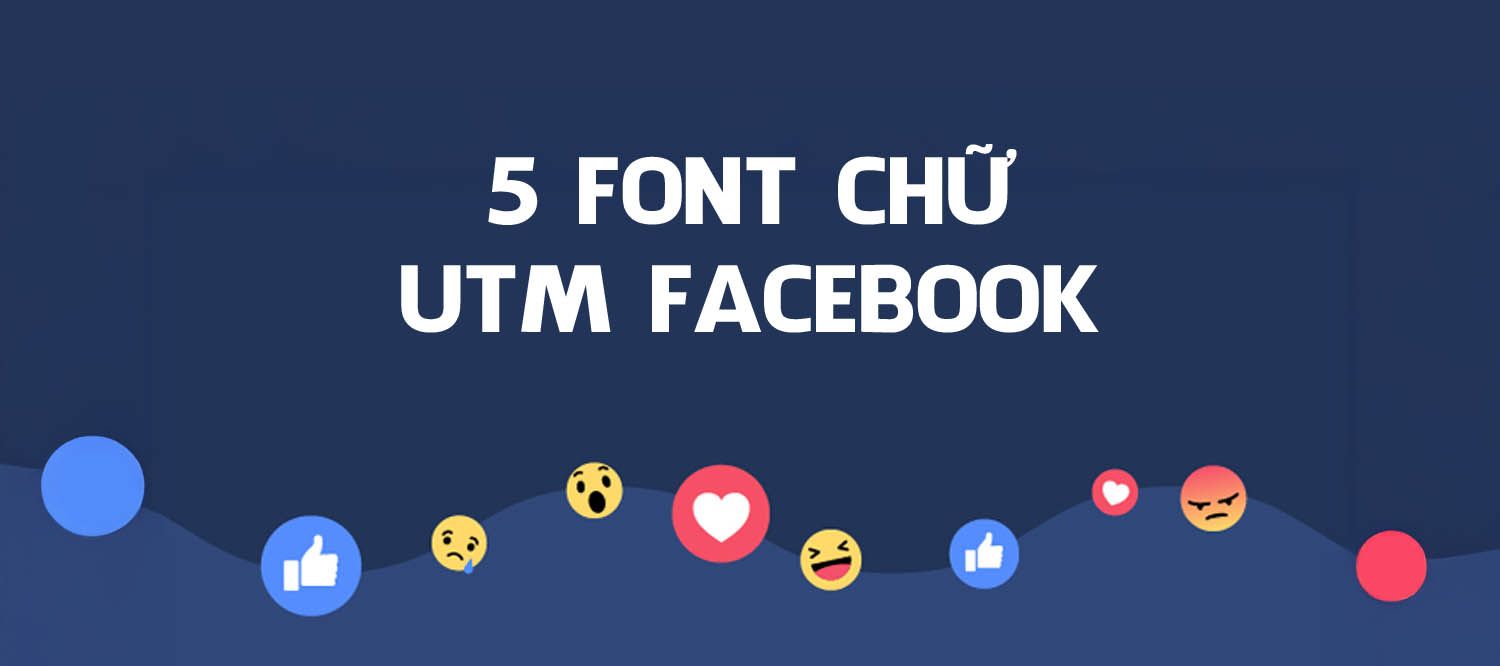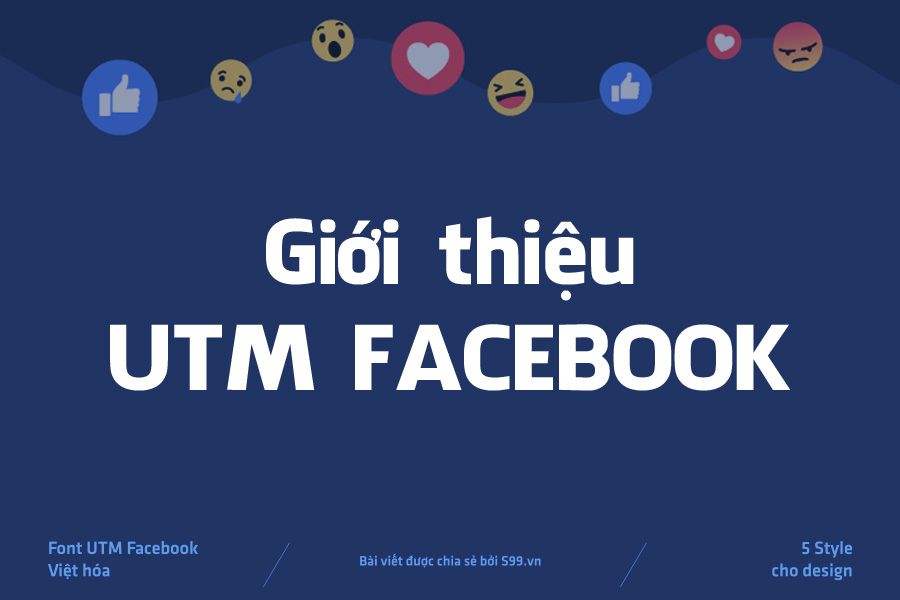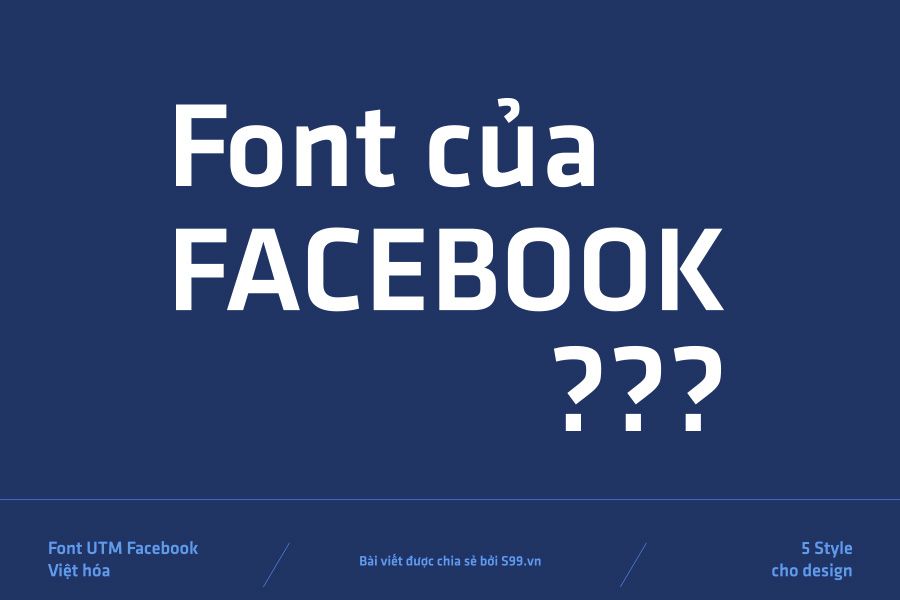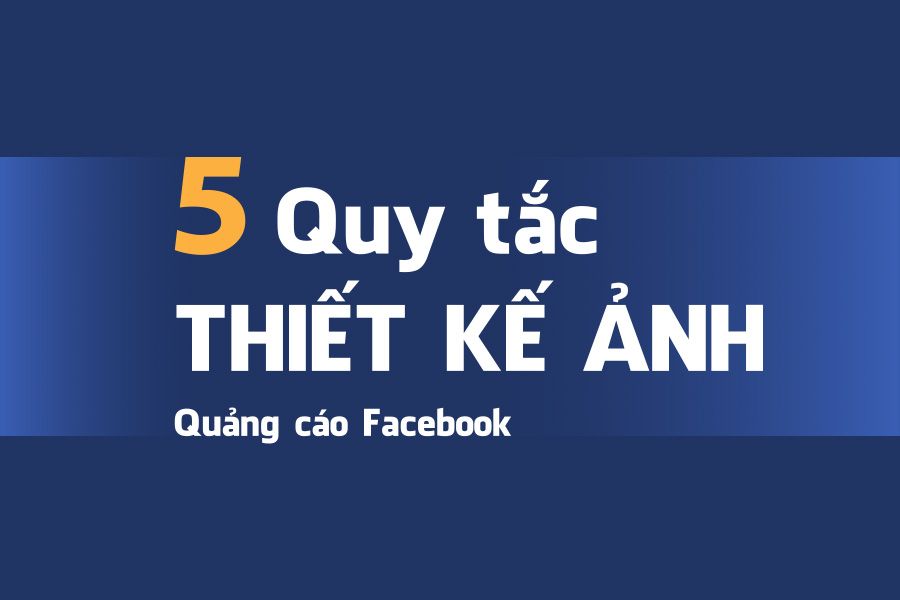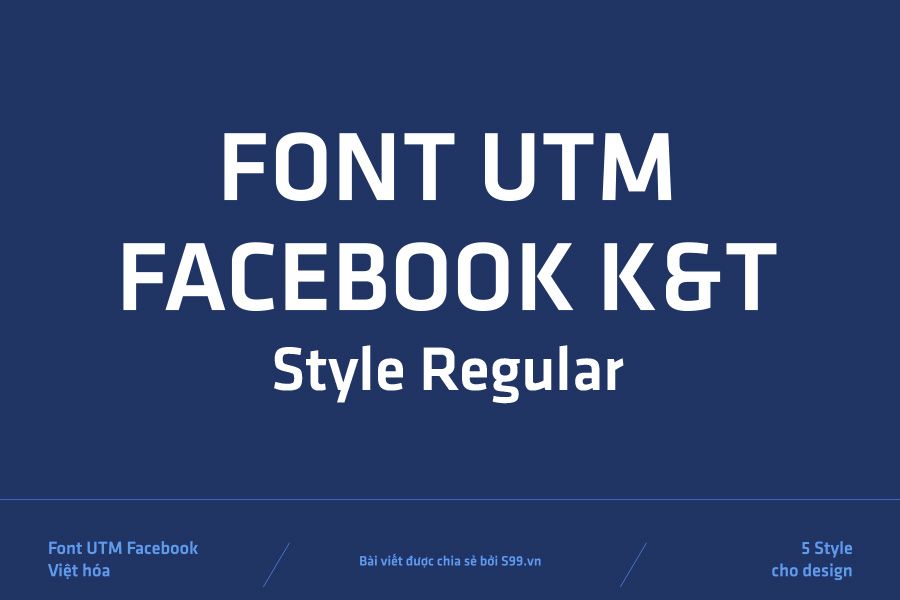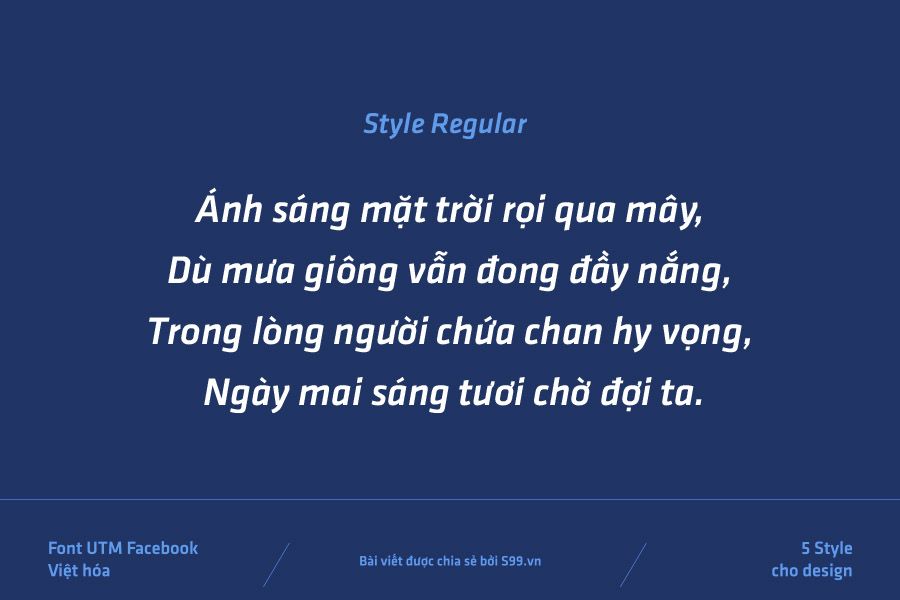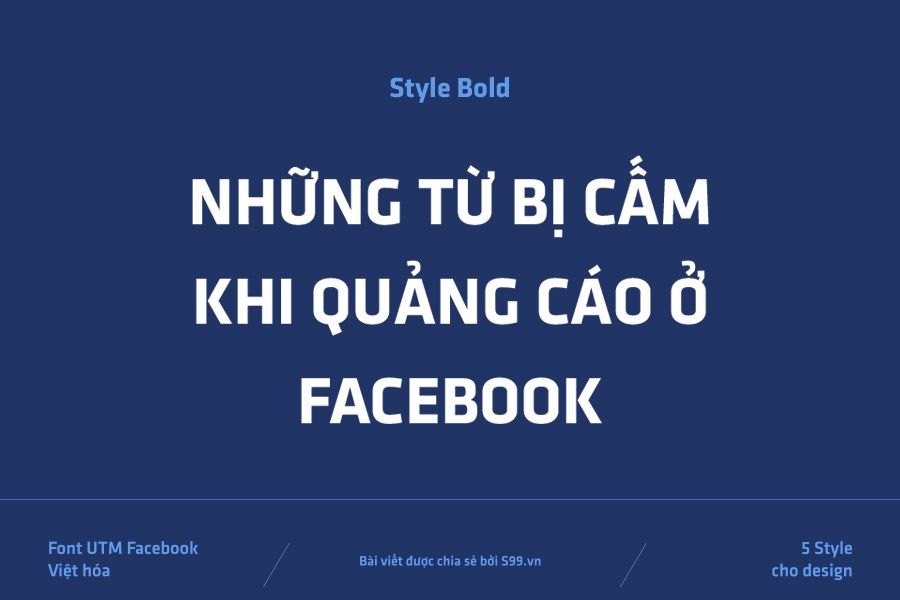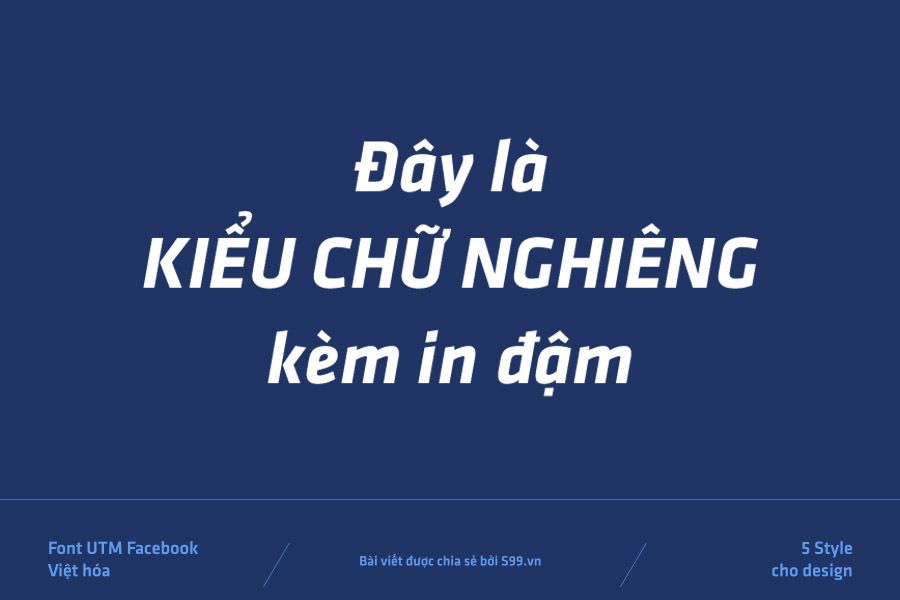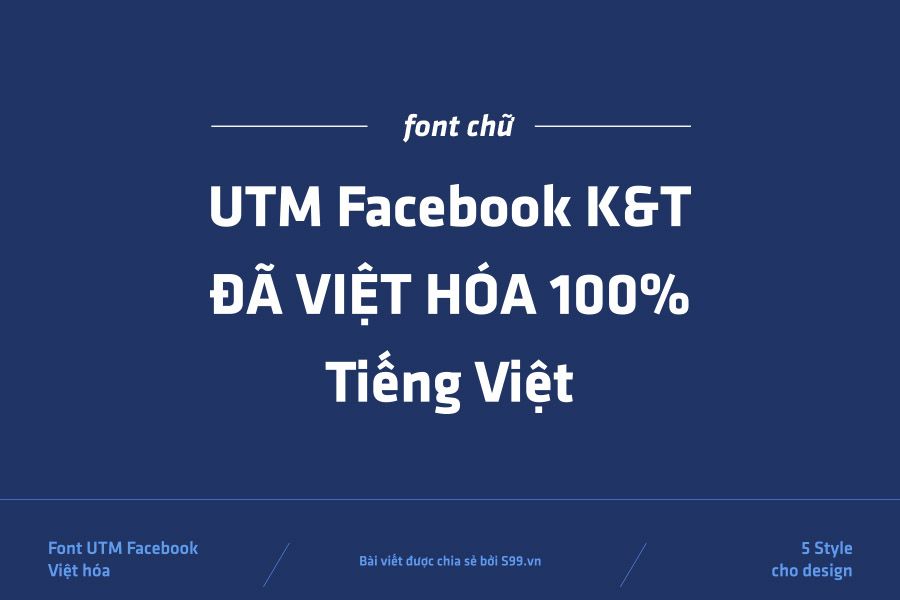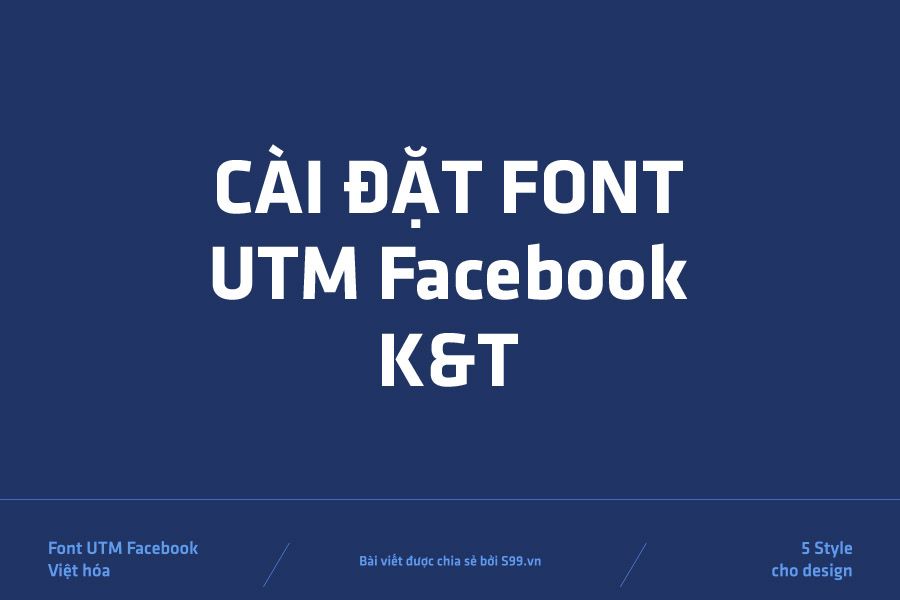
Trong thế giới thiết kế đồ họa hiện đại, font chữ đóng vai trò quan trọng trong việc truyền đạt thông điệp thương hiệu. Trong số đó, font UTM Facebook nổi bật nhờ phong cách sans-serif gọn gàng, hiện đại, hỗ trợ tiếng Việt tốt.
Font UTM Facebook là một dòng sans-serif đơn giản, được Việt hóa bởi Urban Type Management (UTM). Dù mang tên "Facebook", font này không phải là font chính thức của mạng xã hội này, mà được thiết kế dựa trên phong cách gần gũi, trẻ trung và hiển thị tốt trên màn hình.
Không. Font UTM Facebook là font Việt hóa mang phong cách giống font trong giao diện Facebook, nhưng không phải font chính thức do Facebook phát hành.
Kiểu dáng hiện đại, dễ đọc. Dễ ánh xạ, tương thích nhiều màn hình. Hỗ trợ đầy đủ dấu tiếng Việt. Phù hợp nhiều ngôn ngữ thiết kế. Nhiều style linh hoạt như Regular, Italic, Bold...
Bộ font UTM Facebook không chỉ nổi bật bởi khả năng hiển thị rõ ràng, mà còn bởi hệ thống style phong phú, đồng bộ về tỷ lệ, phong cách và cảm xúc thị giác. Nhờ đó, người dùng có thể linh hoạt sử dụng font này cho nhiều mục đích khác nhau như thiết kế in ấn, nội dung số, thương hiệu cá nhân hay truyền thông doanh nghiệp.
Dưới đây là 5 style nổi bật của bộ font UTM Facebook đã được Việt hóa chỉnh chu, mỗi kiểu đều mang bản sắc riêng và phục vụ các nhu cầu thiết kế cụ thể:
Kiểu sans-serif đơn giản, thoải mái. Dễ đọc trên màn hình và in ấn. Phù hợp cho body text, trích dẫn.
Điều chỉnh ký tự K & T hài hòa trong tiếng Việt. Cấu trúc rõ ràng, thoáng đãng. Tốt cho in ấn, slide.
Nghiêng 15 độ, mang cảm giác chuyển động. Tô đậm từ khóa hoặc ghi chú. Dùng cho trích dẫn hoặc slogan.
Nặng, dày, gây ấn tượng mạnh. Lý tưởng cho tài liệu PR, poster, tiêu đề.
Vừa dày vừa nghiêng tạo cảm giác phá cách. Hợp với ngành sáng tạo, thời trang.
Font hỗ trợ đầy đủ dấu thanh, huyền, ngã, hỏi, nặng. Mã Unicode giúp font đọc chính xác trong mọi phần mềm.
Font này rất linh hoạt: dùng trong bài đăng Facebook, story, social post, thiết kế slide PowerPoint, CV, banner, infographic marketing, bao bì sản phẩm, tem nhãn.
Font được Việt hóa bởi nhóm Urban Type Management (UTM). Tác giả gốc của font là Rui Abreu, một nhà thiết kế font chữ nổi tiếng người Bồ Đào Nha, với phiên bản gốc mang tên Arsenal. Sau quá trình Việt hóa, font được đổi tên thành UTM Facebook và được điều chỉnh lại một số ký tự để phù hợp với ngữ âm và ngữ pháp tiếng Việt.
Không. Facebook sử dụng font tùy giao diện như SF UI, Segoe UI. Font UTM Facebook chỉ giống phong cách thiết kế.